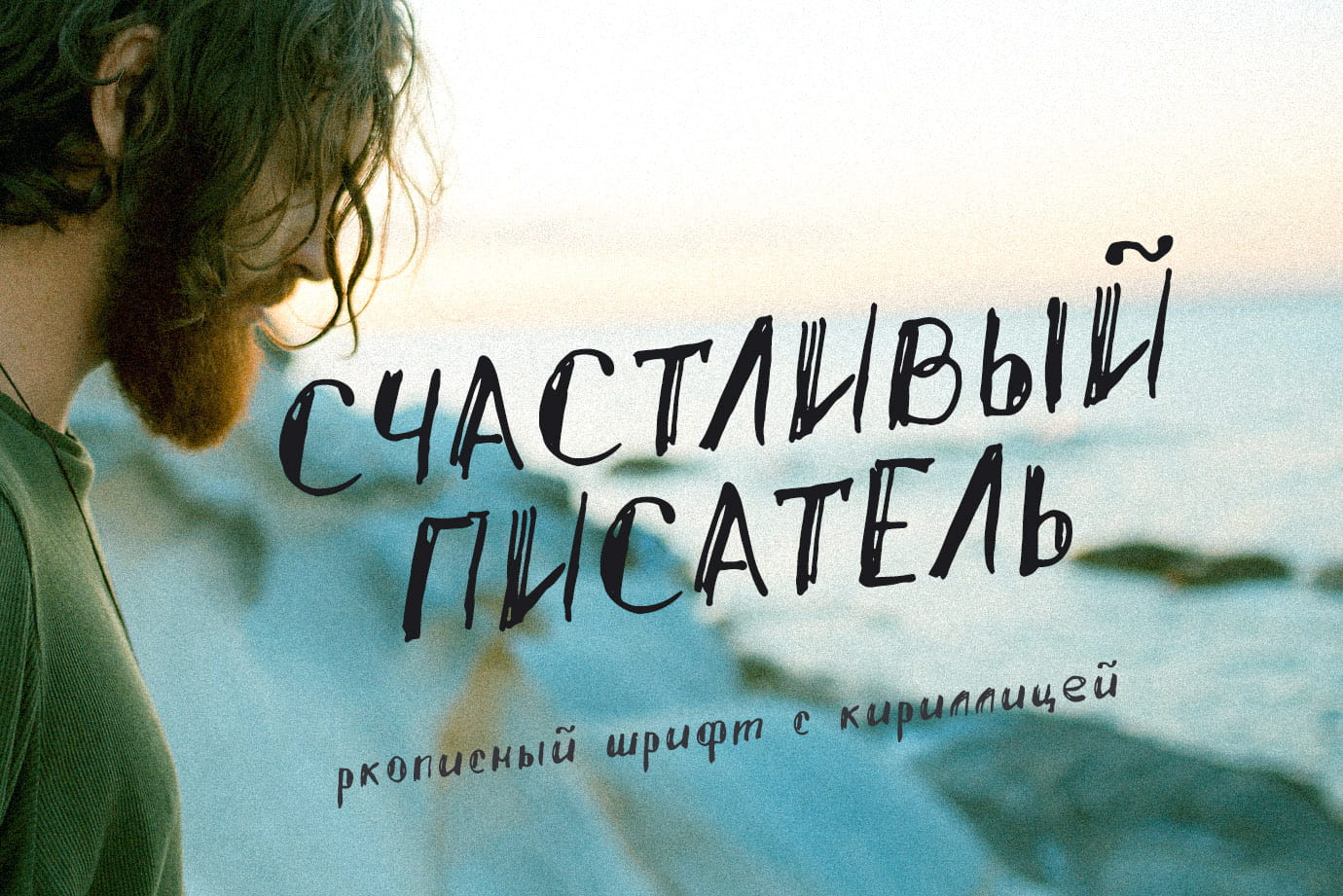
Это ДИКИЕ БУКВЫ (WILD WORDS) — рукописный шрифт, написанный высыхающим маркером. Буквы этого шрифта, кажется, танцуют какой-то дикий безумный танец. Шрифт имеет ярко выраженную текстуру маркера, заглавные и строчные буквы сочетаются друг с другом, поэтому вы можете использовать все возможные их комбинации в одном слове, он очень аутентичен, содержит большое количество лигатур и альтернативных символов. Поддерживает множество языков, включая кириллицу.
Шрифт идеально подходит для:
- Дизайна логотипа и фирменного стиля
- Упаковки и брендинга
- Рекламных материалов и плакатов
- Дизайна продукта, веб-сайтов и блогов
- Постеров, соцсетей, принтов на одежде
ДИКИЕ БУКВЫ (WILD WORDS) поддерживает множество языков, включая английский, французский, немецкий, итальянский, испанский, португальский, датский, норвежский, шведский, финский, эстонский, турецкий, романскую группу и кириллицу.